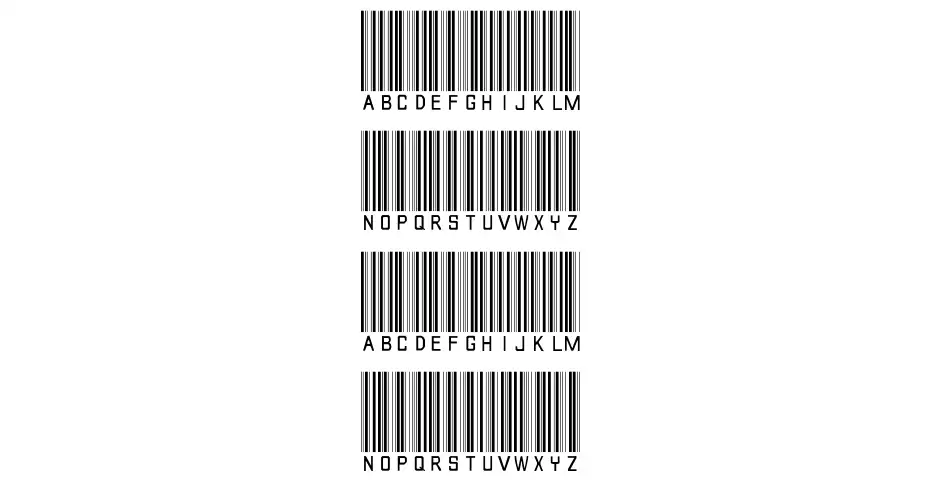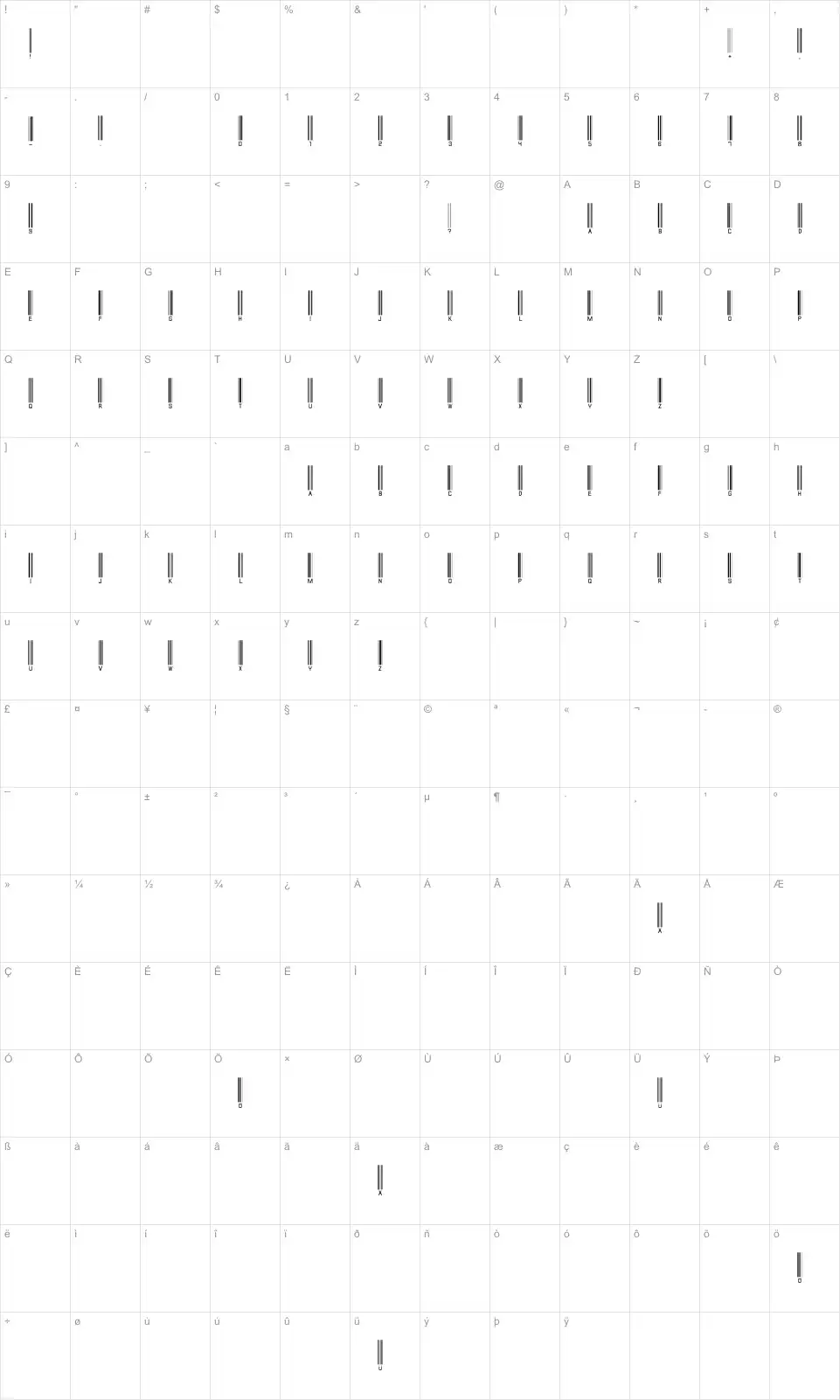
A fonte Barcode Font, criada por anke-art, é perfeita para quem precisa de um elemento visual criativo e eficaz. Se você está procurando por um design único e moderno, essa fonte será uma excelente escolha. Feita na categoria de Dingbat e dedicada ao uso de códigos de barras, a fonte Barcode Font oferece uma versão gratuita que pode ser baixada diretamente para uso pessoal ou comercial. A fonte está disponível em formato TTF, tornando-a compatível com diversos programas de design e impressão. A anke-art adicionou a fonte à sua base em 11 de julho de 2022, e atualmente já foram baixados mais de 26.900 cópias. Se você deseja experimentar a forma como essa fonte aparecerá em seu projeto, pode gerar um preview personalizado online. Além disso, a fonte Barcode Font está licenciada como Donationware, permitindo que você contribua financeiramente se desejar expandir a base de usuários do designer. Com um tamanho de 7 KB, esta fonte é compacta e ideal para projetos que precisam de uma solução leve e eficaz. Visite o site do designer, anke-art.de, para explorar mais recursos criativos.
Designer: anke-art